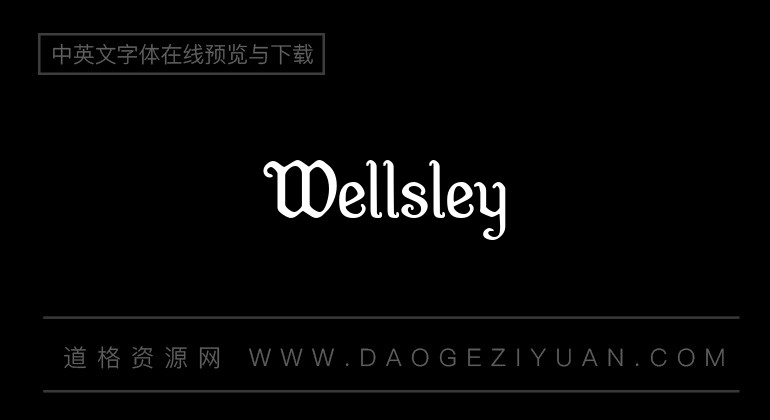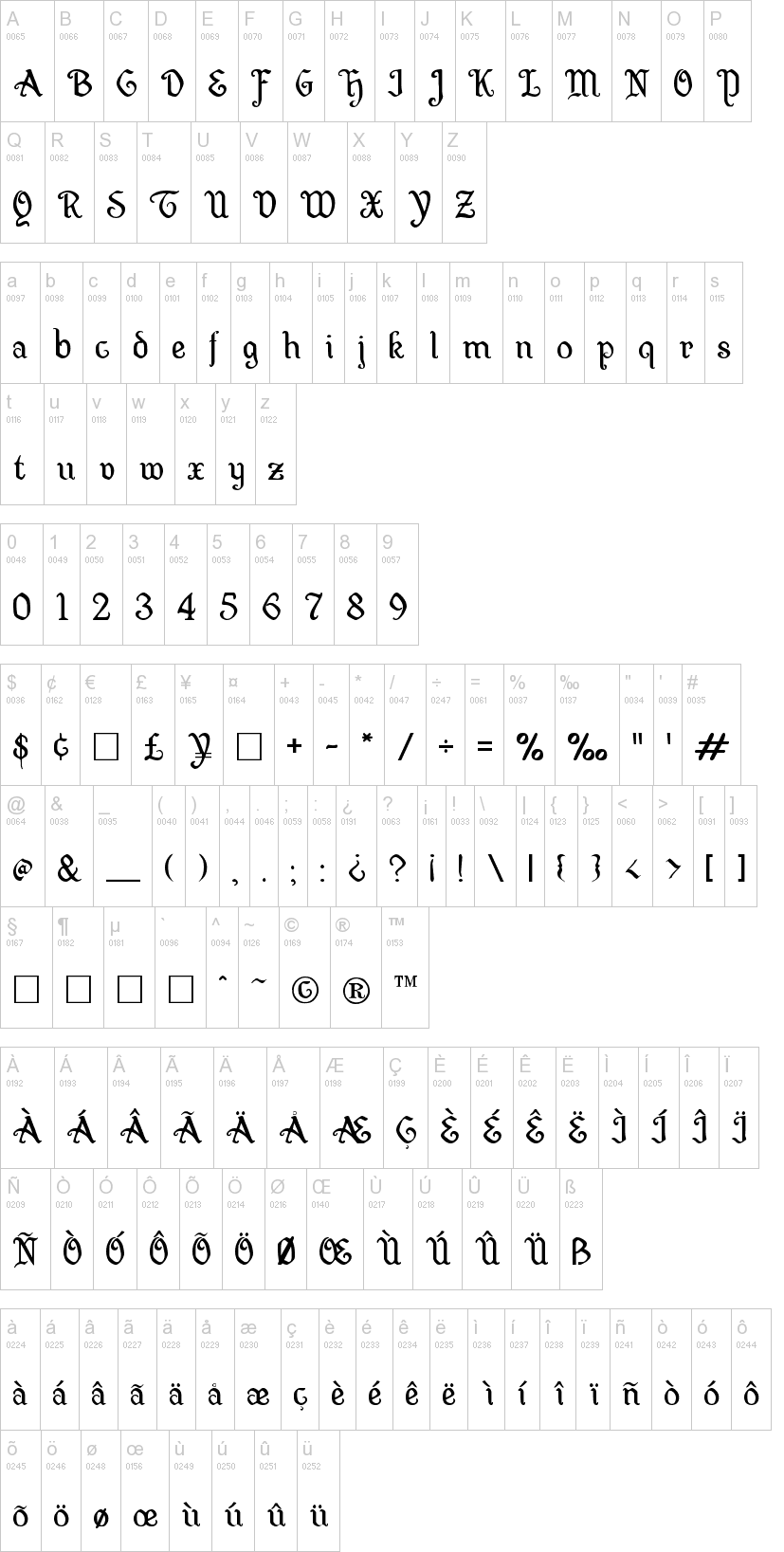
Wellsley 字体是一款经典的英文字体,它的字母形状细腻而优雅,拥有良好的节奏感。它拥有经典的英文字母,细腻的笔画,优雅的曲线,以及清晰的细节,使它成为一款有趣而优雅的字体。Wellsley 字体适合用于书籍,杂志,报纸,广告,海报等印刷媒体,也适合用于网页设计,图形设计,印刷设计等等。内容介绍
Wellsley是一款非常不错的手写艺术字体,具有很好的视觉感,适合于文化类的宣传设计、商业类品牌的广告和产品包装设计以及个性化文字排版等较多场景。